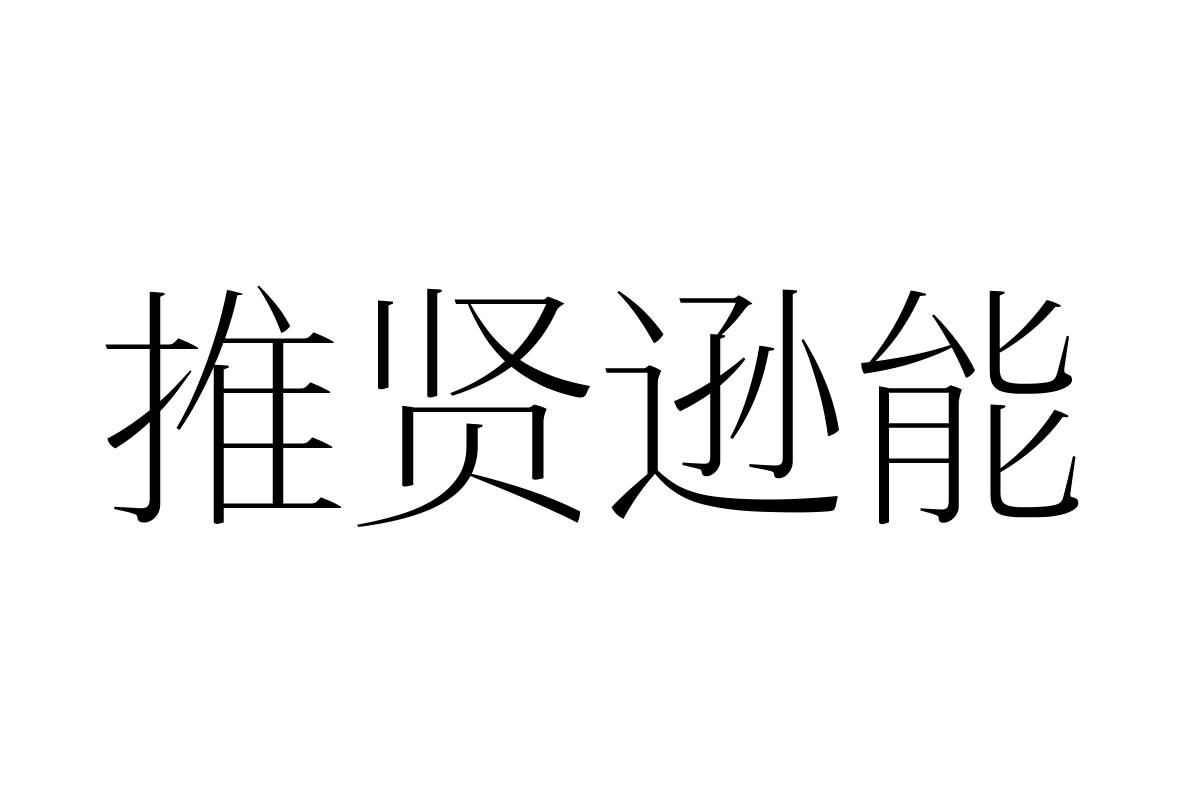
汉仪瑞意宋35W是一款现代的中文字体,具有独特的艺术风格和设计感。这款字体采用了简洁而富有力量的设计,线条流畅,结构紧凑,给人以强烈的视觉冲击力。
字体特点:
1. 字形优美:汉仪瑞意宋35W的字形线条流畅,结构紧凑,给人一种优雅而有力的感觉。
2. 笔画清晰:每个字的笔画都清晰可见,易于阅读和识别。
3. 风格独特:该字体具有独特的艺术风格,适合用于需要强调个性和创意的场合。
4. 适用范围广泛:适用于各种印刷媒体,如报纸、杂志、书籍、广告等。
总的来说,汉仪瑞意宋35W是一款具有现代感和艺术风格的中文字体,适合用于需要强调个性和创意的场合。